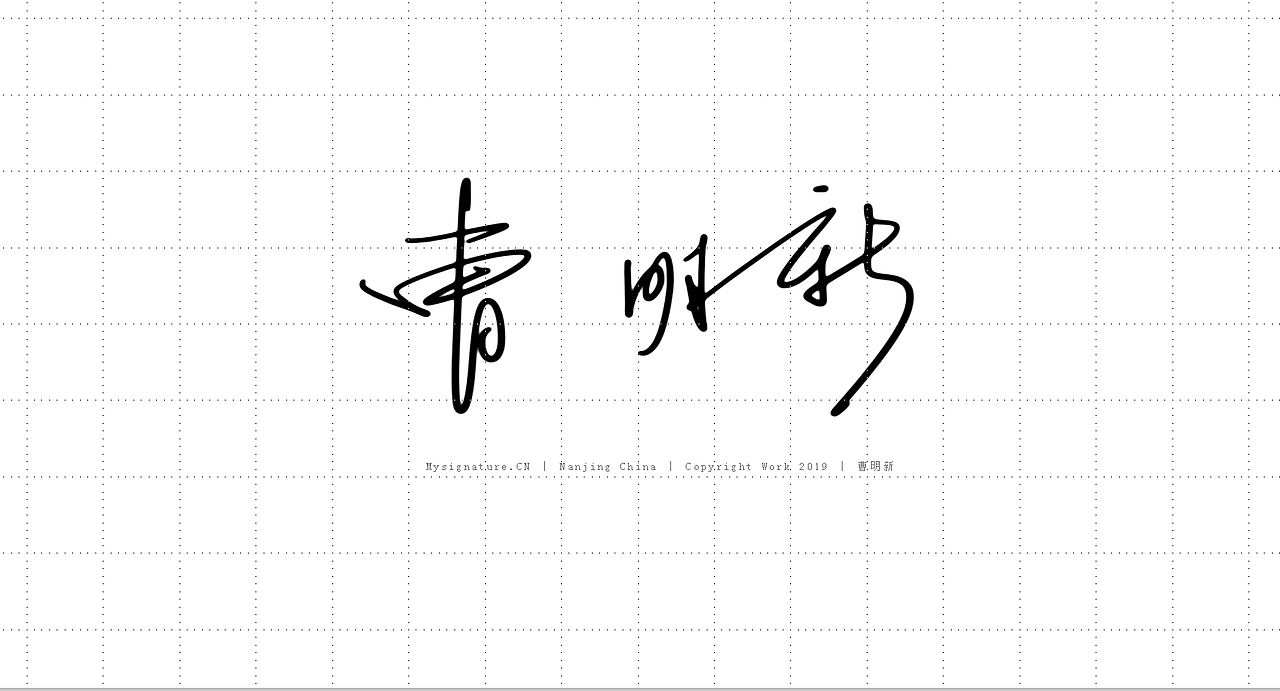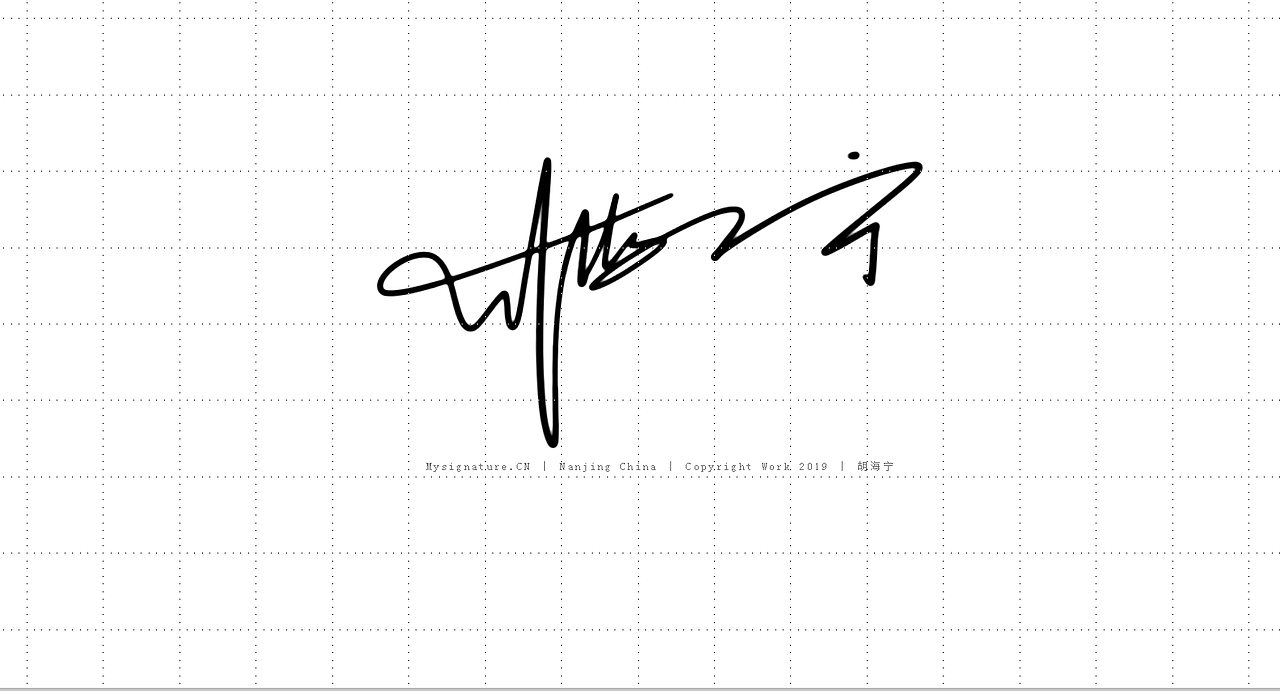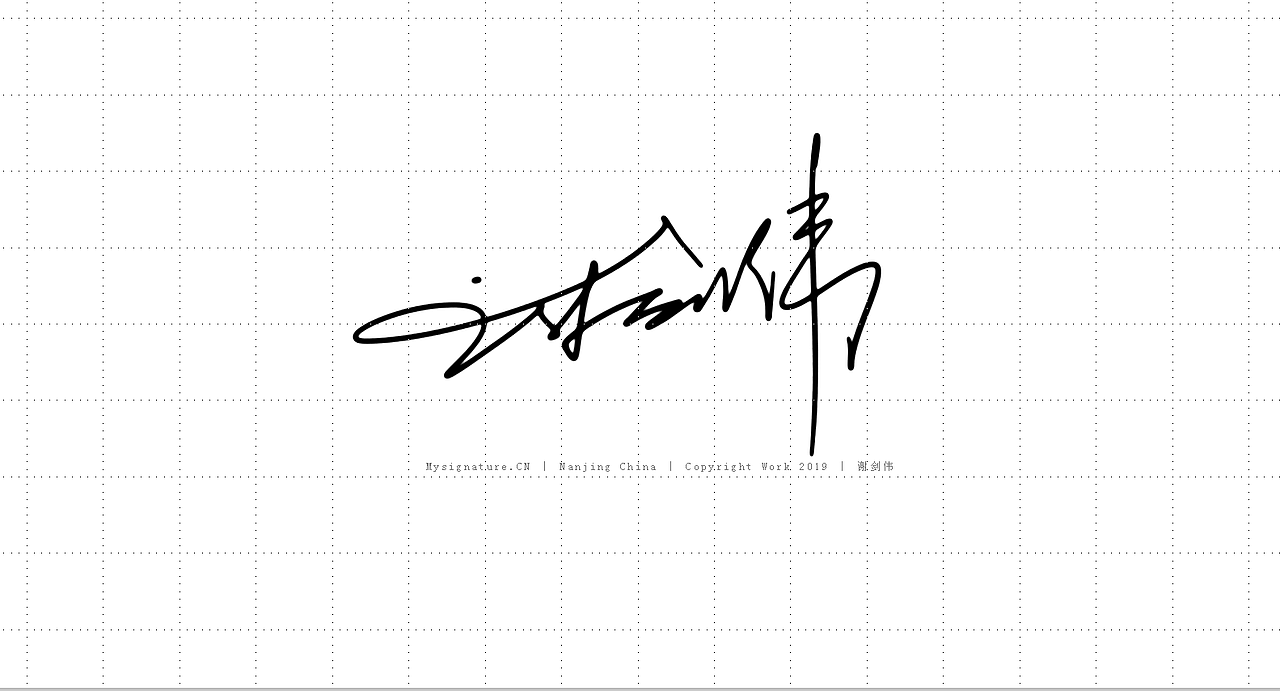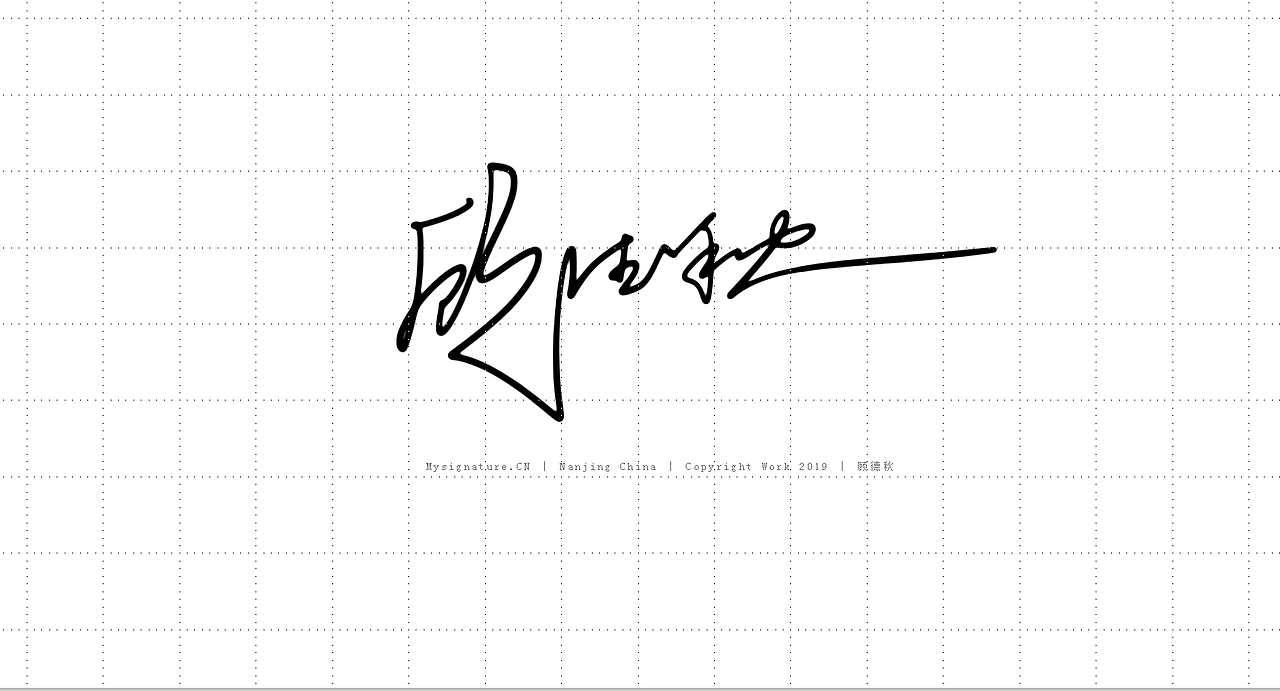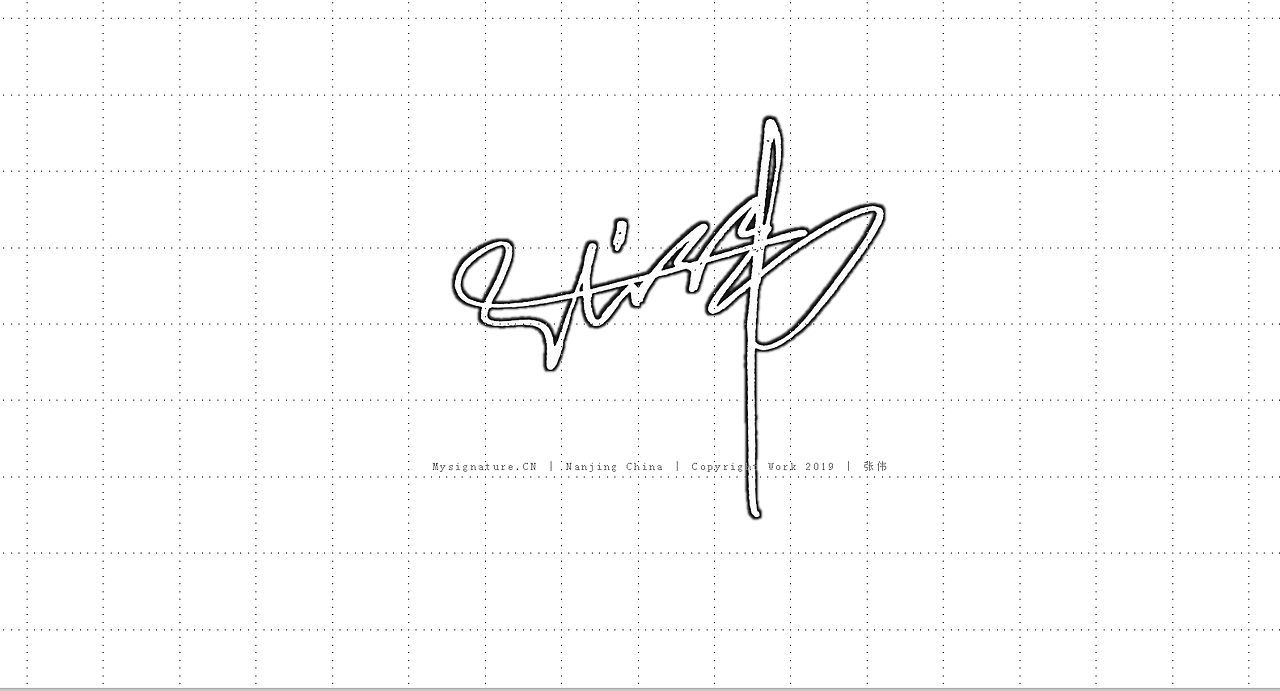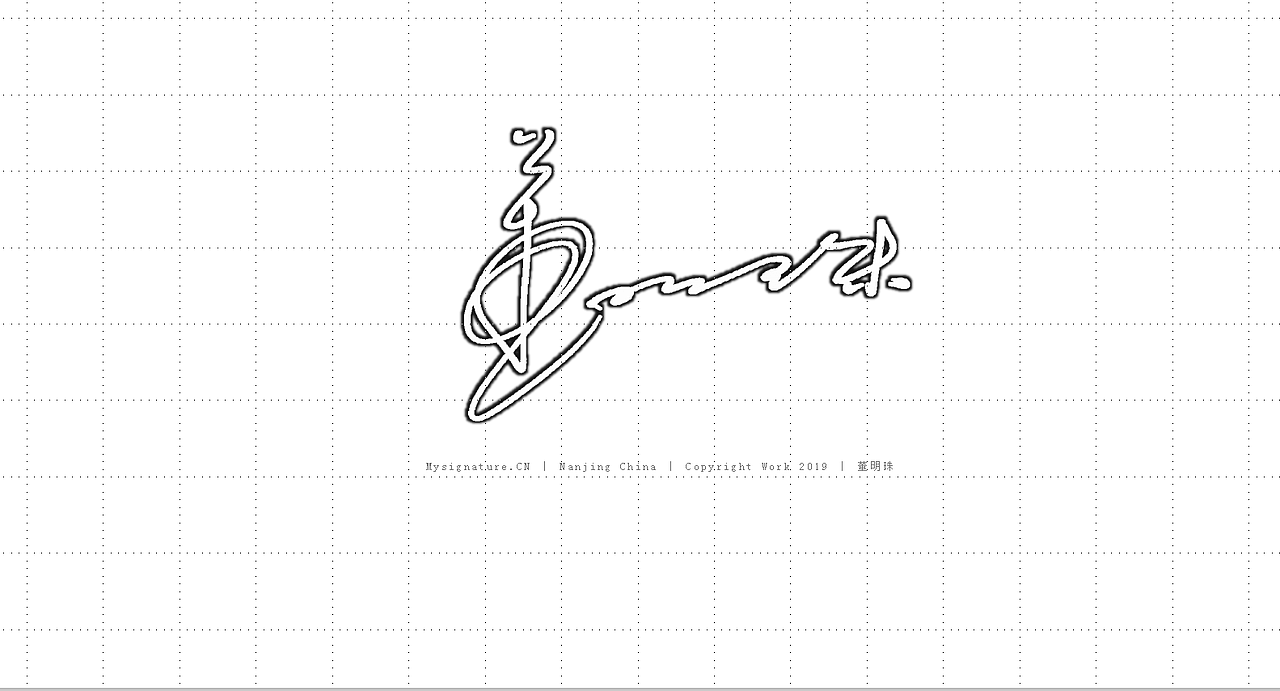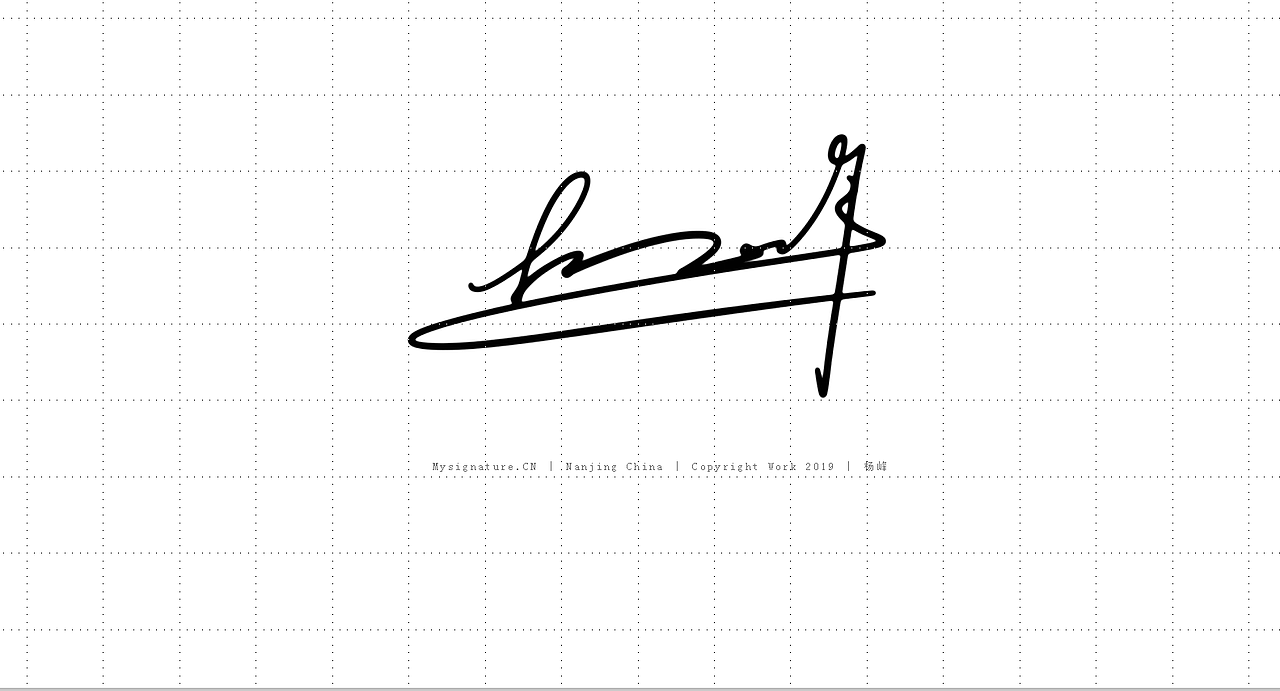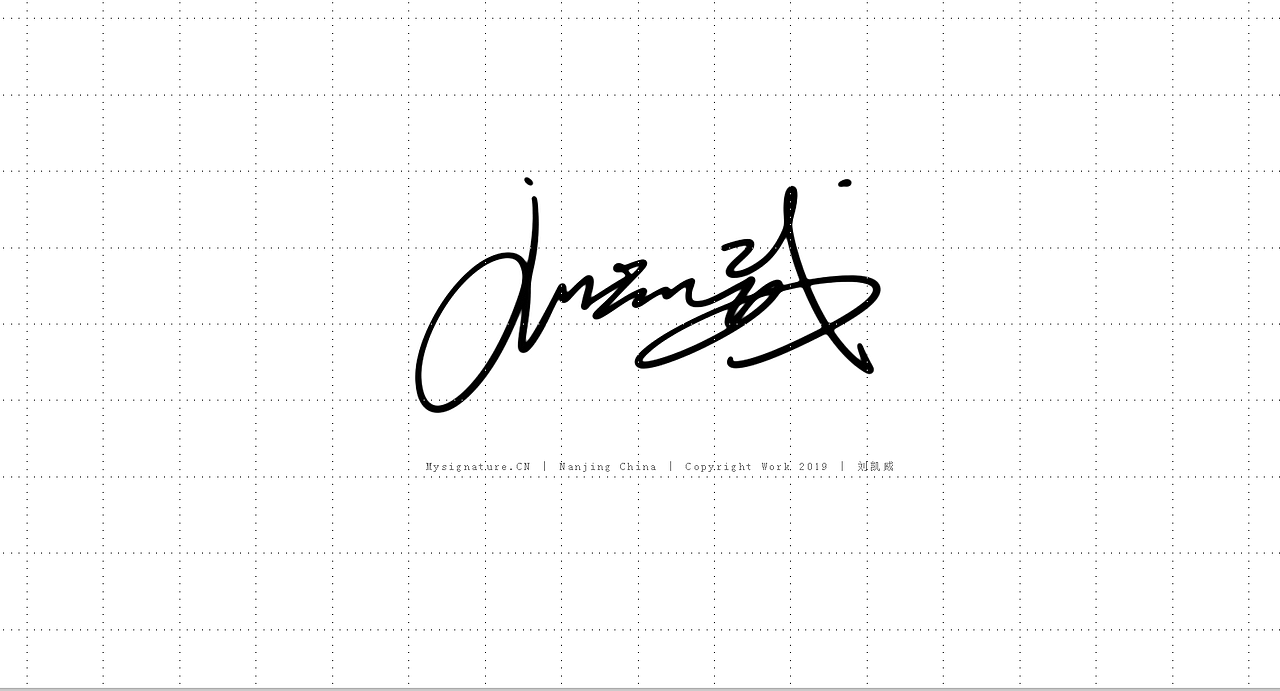
商务风格签名设计丨合同签名丨防伪签名丨工作签名设计
满足日常工作实际需求
Meet daily needs
签名在现实生活中应用极为广泛:合同与银行信用往来、填写简历、会议签名、合同签字、物流签收确认签字、信用卡刷卡签字、明星签名等,几乎无处不在。。。从普通人到国家政要,从最普通签收快递签字到国家双边合作签署重要文件,都需要用到签名!
社会的法律化和文明的进程,使签名成了代表个人资信和形象的识别符号,需要我们频繁地使用。因此,一款心仪的签名对一个人来说,何等重要!
优化签名书写·提升工作效率·体验书写乐趣
Optimize writing & efficiency & experience writing pleasure
现实生活中,特别是一些企业老总,医生,明星等特殊群体,这些人群会经常用到签名署名,但是由于名字是由长辈赐予的,不可避免的有很多人的名字会很复杂,按照正常书写笔画几十笔,如果通过优化设计,一些名字两三笔就可以写好,同时名字之间的联系还更加优美紧密!通过签名设计师的优化设计,使得签名书写的效率得以提升,同时又能增强签名整体的视觉审美效果!